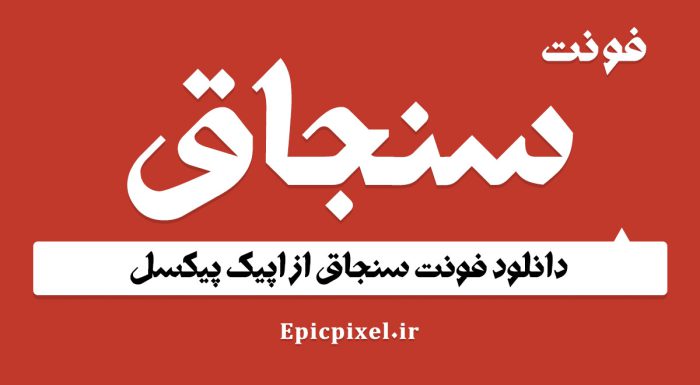
فونت سنجاق یک فونت نمایشی با الهام از خط نسخ
فونت سنجاق یک فونت نمایشی است که از خط نسخ الهام گرفته . این فونت در 3 وزن مختلف طراحی شده و مناسب برای طراحی متنهای کوتاه و عنوانبندی است. ایده کلی تایپفیس سنجاق با الهام از فرم سنجاق بدست آمده است. سنجاق متشکل از منحنیها، تیزیها و شکستگیها با ضخامتهای نسبتاً پر کنتراست است. خطوط شکسته و اریب عمدتاً با زوایای چهل و پنج درجه در اتصال به منحنیها، فرمی جسورانه و در عین حال پرجنب و جوش را برای این شکل قلم ایجاد کرده است.
ویژگیهای فرمی فونت سنجاق
فونت سنجاق دارای چندین ویژگی فرمی است که آن را از دیگر فونتهای نسخ متمایز میکند. برخی از این ویژگیها عبارتند از:
ضخامتهای متفاوت و تناسبات ساختاری
حروف وزن های مختلف فونت سنجاق دارای اسکلت، تناسبات ساختاری و محورهای رسامی مشترک هستند. البته افزایش ضخامت در وزن سنگین قلم ناگزیر باعث تغییر نامحسوس شکل چشمیها شده است. حروف در وزنِ سبُکِ سنجاق، اندامی استخوانی با فضاهای منفی باز دارند و اما در وزن سنگین آن، پر چگالی و فشرده هستند. یکی دیگر از شاخصههای فرمی این قلم، لحاظ یک ضخامت ثابت برای نازکترین قسمت آناتومی حروف در دو وزن سبک و سنگین است
دانلودزوایا، قوسها و پایانههای یکسان
دیگر خصیصه در کنار زوایا، قوسها و پایانههای یکسان حروف، باعث نظم هندسی بیشتر فونتِ سنجاق شده است. هر بخش از آناتومی حروف بر اساس یک الگو یا مبنای ثابت فرمی طراحی شده است: به بیان سادهتر، تمام قوسهای مثبت (ص، ن، ل، ی…) تمام قوسهای منفی (ع ،ح …)، تمام خطوط عمود (ا،ط،ل …)، تمام چشميها (ه، م،) و … در دستۀ خود مشابه یکدیگر هستند.
ليگيچرها و شكل دوم برخي حروف
فونت سنجاق شامل لیگیچرهای متعددی (ترکیبات دو تایی حروف) است که به صورت خودکار یا با اضافه کردن همزه پس از حرف اول فعال میشوند. برخی از این لیگیچرها عبارتند از: آل، آم، آن، آه، آو، بل، بم، بن، به، بو، پل، پم، پن، په، پو و … همچنین برخی حروف در فونت سنجاق دارای شکل دوم هستند که با استفاده از همزه قبل از حرف فعال میشوند. برخی از این حروف عبارتند از: ت، ث، ج، خ، ذ، ز و … این شکل دوم حروف به منظور جلوگیری از تداخلات فرمی و بهبود خوانایی متن در برخی موارد استفاده میشود.
کاربردهای فونت سنجاق
فونت سنجاق به دلیل شکل نمایشی و جذاب خود مناسب برای کاربردهای مختلف طراحی گرافیک است. برخی از این کاربردها عبارتند از:
تایپوگرافی، عنوانبندی و لوگوتایپ
فونت سنجاق به خاطر داشتن شکل هندسی و قابل تشخیص خود مناسب برای تایپوگرافی و عنوانبندی است. این فونت میتواند با استفاده از رنگها و تغییرات در سایز و جهت حروف تاثیر گذار باشد. همچنین فونت سنجاق به دلیل داشتن شخصیت قوی و منحصر به فرد خود مناسب برای طراحی لوگوتایپ است.
متننويسي و طراحي براي زبان عربي
فونت سنجاق به دليل پشتيباني كامل از گليفهاي مورد نياز زبان عربي نيز قابل استفاده براي متننویسی و طراحی برای زبان عربی نیز قابل استفاده برای متننویسی و طراحی گرافیک است. این فونت میتواند با توجه به ویژگیهای خط نسخ، متنهای عربی را با زیبایی و خوانایی بالا نمایش دهد.
دانلودهماهنگي با فونتهاي لاتين كلاسيك
فونت سنجاق به دليل داشتن شكل هندسي و پر كنتراست خود هماهنگي خوبي با فونتهاي لاتين كلاسيك دارد. اين فونت ميتواند با فونتهاي لاتين مانند Bodoni، Didot، Garamond و … تركيب شود و تعادل بين زبانها را حفظ كند.
فونت سنجاق با چه فونتهای دیگری همخوانی دارد؟
فونت سنجاق با فونتهای دیگری که دارای شکل هندسی و پر کنتراست هستند همخوانی دارد. برخی از این فونتها عبارتند از: Futura, Helvetica, Arial, Roboto, Montserrat و … . البته بستگی به محتوا و هدف طراحی دارد که چه فونتهایی را با هم ترکیب کنید.
فونت سنجاق چگونه طراحی شده است؟
فونت سنجاق با استفاده از نرمافزار FontLab Studio طراحی شده است. این نرمافزار یک ابزار قدرتمند برای طراحی و ویرایش فونتهای مختلف است. طراح فونت سنجاق با توجه به ایده کلی تایپفیس سنجاق با الهام از فرم سنجاق، ابتدا حروف را به صورت دستی رسم کرده و سپس با استفاده از نرمافزار، حروف را دیجیتال کرده و بهینهسازی کرده است. طراح همچنین با توجه به قواعد خط نسخ، لیگیچرها و شکل دوم برخی حروف را نیز طراحی کرده است.